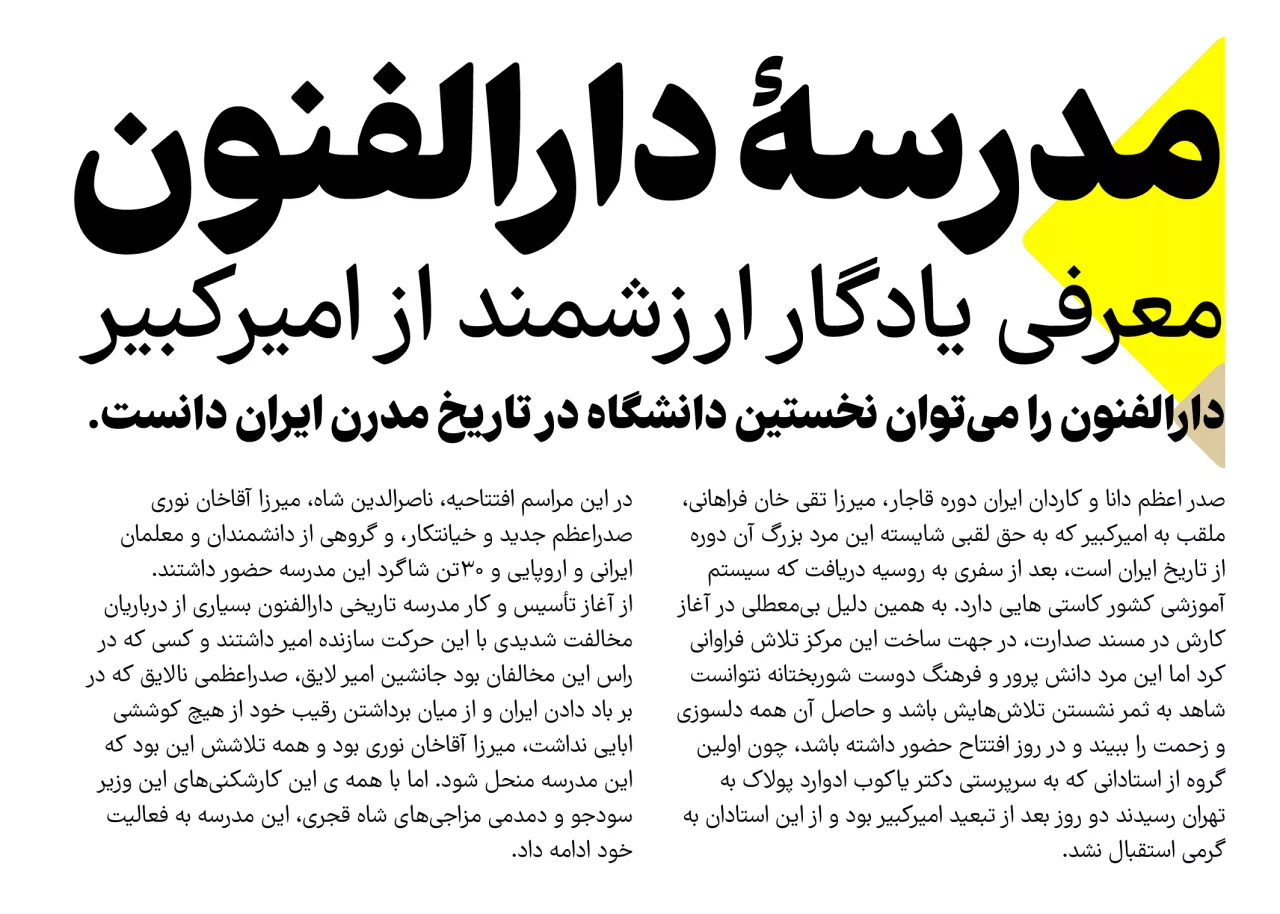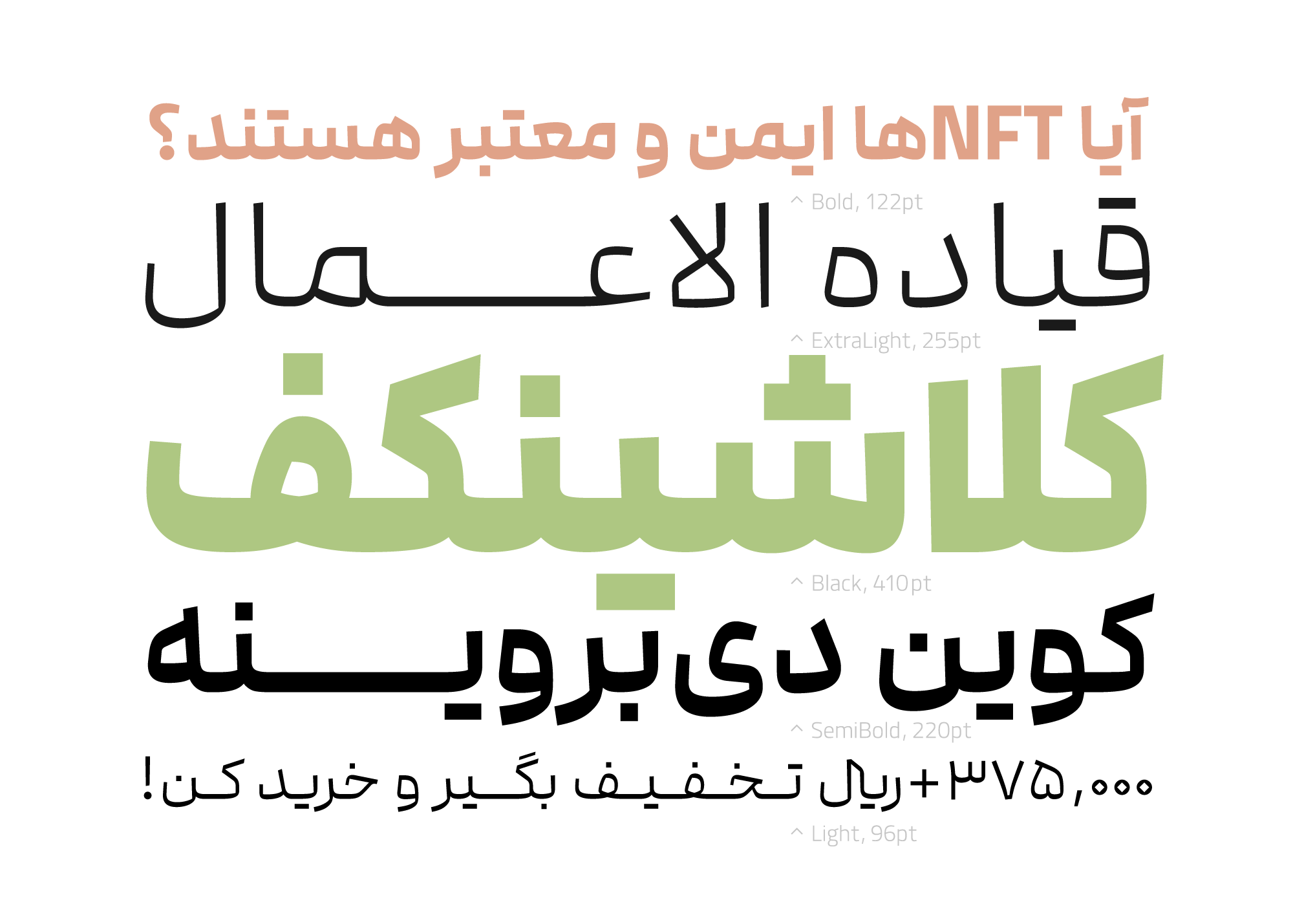
وریبل فونت چیست ؟ (variable font) ساده و روان
وریبل فونت چیست ؟
سلام دوستان توی این مقاله می خواهیم بهتون خیلی ساده و خلاصه و روان این قابلیت پرفایده که چند سالی میشه وارد عرصه تایپوگرافی شده رو واستون آموزش بدیم. از معنیش یک مفهوم کلی به ذهن میاد . وریبل که همون میشه متغیر یعنی فونت متغییر یا فونت وریبل.
ازسال 2016 واسه ایجاد مزیت هایی و فوایدی که جلوتر خدمتتون میگم. چند شرکت اومدن یک نسخه جدید از Open Type رو ارائه کردن . از اونجایی که فونت ها دارای چندین وزن و هر وزن یک فایل مجزا واسه خودشون دارن گفتن که همه فایل ها در یک فایل به مشتری ارائه بشه.
پس تا اینجا فهمیدیم که فونت وریبل یا متغییر همون پیکیج کاملی از فایل های مجزای هر وزن از خانواده یک فونت یا تایپ فیس که دیگه یک فایل شده ولی همه وزن ها و حتی اعداد و علائم و نقطه گذاری و … رو داخل خودش به همراه داره.
حجم کمتر سرعت بیشتر فونت های متغییر
همه میدونیم جهان ما با پیشرفت تکنولوژی داره به سمتی میره که هم کار ها سریعتر و جمع و جور تر و خیلی ساده بخوایم بگیم آسون تر بشه. وریبل فونت یا فونت متغییر همون چیزی بوده که طراحان با هدف های گفته شده به دنبالش بودن و اون رو خلق کردن.
یک صفحه وب رو در نظر بگیرین با یک فونت معمولی. فرض کنین توی این صفحه تیترها با وزن bold متن ها با وزن regular و قسمت های داخلی تر هم با وزن light به نمایش در میان. 3 حجم مجزا واسه هر وزن فایل و 3 درخواست مجزا هم واسه هر وزن به سرور ارسال میشه . البته چیزاهای دیگه هم وجود داره که وارد جزئیات نمیشیم.
حالا با یک نسخه وریبل حجم به یک فایل و تعداد درخواست هم به یک بار کاهش پیدا میکنه . فکر کنم دیگه الان مشخص شد که مزیت های وریبل فونت چیه و چقدر مفیده.
معرفی نمونه ای های از وریبل فونت های زیبا
نحوه استفاده از وریبل فونت ها در نرم افزار های طراحی
همانطور که قبلا گفته شد نسخه های متغییر دارای یک فایل و دارا بودن همه وزن های طراحی شده ، علائم نگارشی ، نقطه گذاری های مختلف و کشیدگی … در دل خود می باشند . حال نحوه استفاده از آنها در نرم افزار های طراحی حرفه ای مانند ایلسترتور یا فتوشاپ بسیار ساده و راحت می باشد.